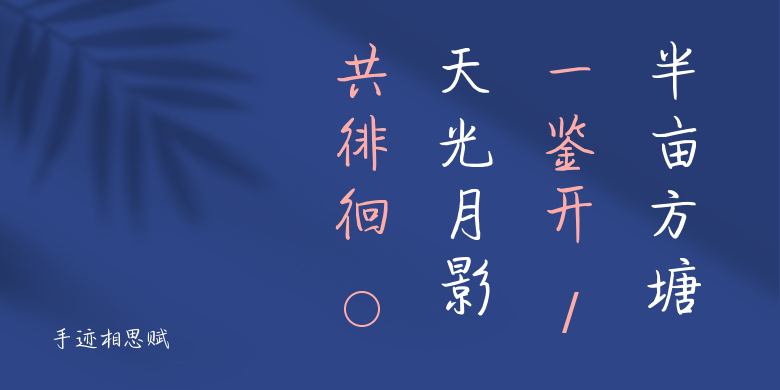
手迹相思赋
手迹相思赋,这款字体结构工整、笔画清晰,兼顾美观与易读性,适用于标题、正文、海报、包装、LOGO 等多种场景。字形优雅稳定,风格百搭耐看,适配日常排版与创意设计,让文字呈现更舒适、更具质感。手迹相思赋一笔一画,皆是细节,以均衡的比例、流畅的线条打造舒适视觉体验,字形端正大气,风格简约现代。无论是商业设计、品牌宣传还是日常排版,都能轻松驾驭,让文字更有格调与力量。手迹相思赋字体下载。